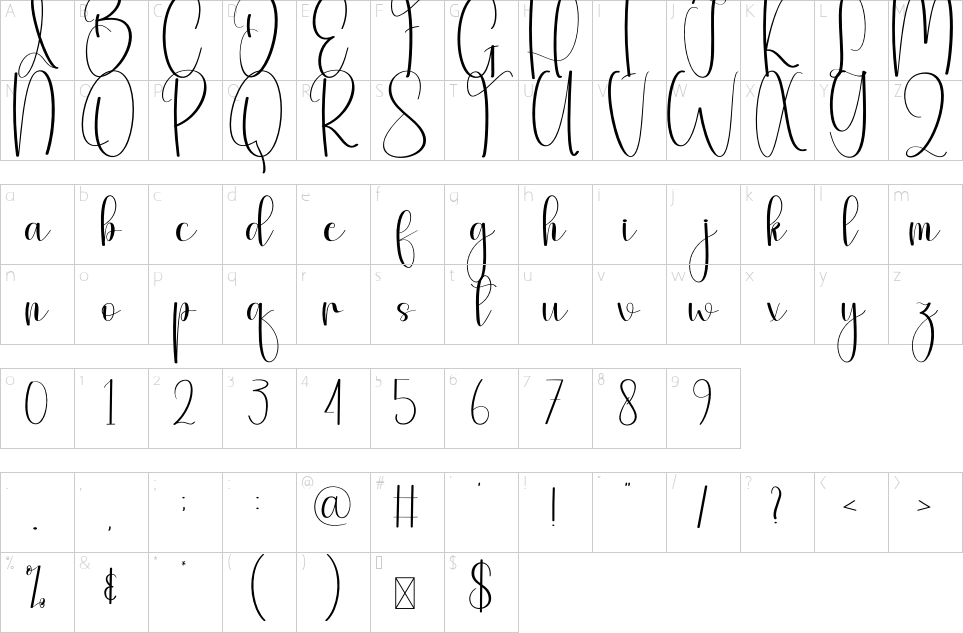
Aqui está uma versão contendo 2 parágrafos curtos para a descrição do arquivo de fonte ‘Gratitude Font – 1001 Free Fonts’, mantendo-se fiel à descrição original: Sinta-se gratificado com o design desta novíssima fonte gratuita. O ‘Gratitude Font’ foi projetada por William Jhordy e está disponível para download tanto em versão Windows quanto Mac, proporcionando uma escolha de estilo visual fácil e acessível. Este material é um excelente adorno para qualquer projeto que necessite de uma fonte agradável e versátil, sendo particularmente útil quando buscamos uma forma elegante de expressar gratidão na design gráfico. A cada instante, a busca por recursos gratuitos como esta font nos leva a novas possibilidades criativas.